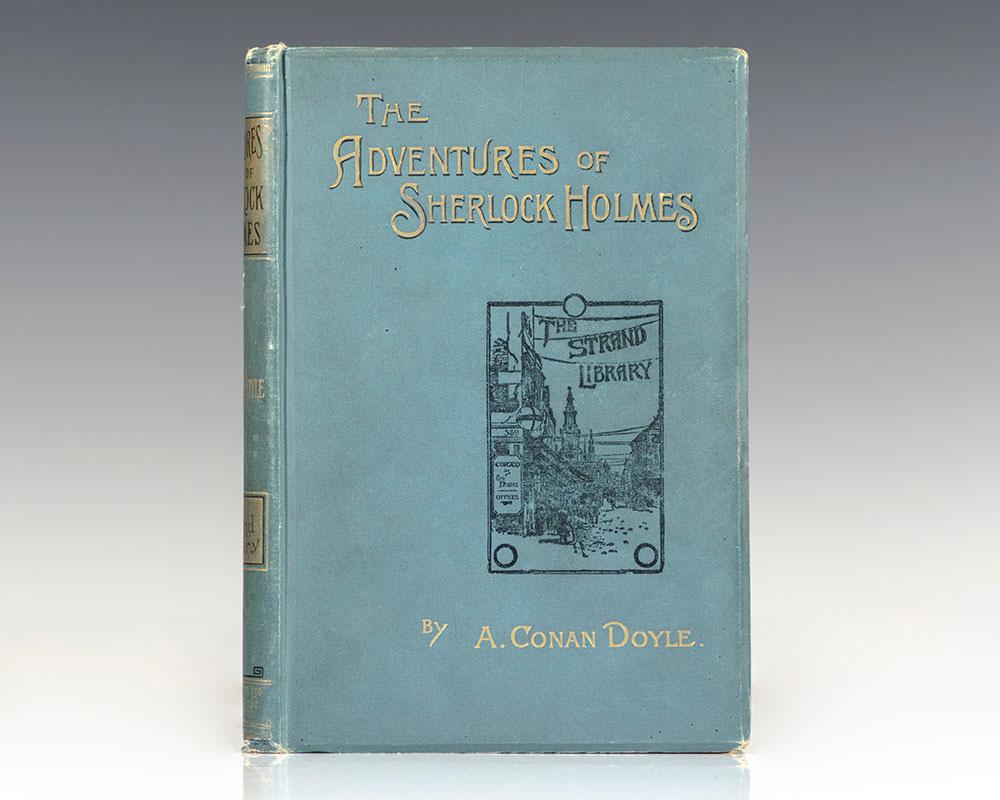
Titelschrift von Erstausgabe "Sherlock Holmes" gesucht
ich suche eine Schrift, die jener der Erstausgabe von A. Conan Doyles "The ADVENTURES of SHERLOCK HOLMES" nahe kommt. Die Erstausgabe stammt von 1892 und wurde in London herausgegeben. Die Illustrationen im Buch stammen von Sidney Paget. Was historische Schriften angeht, bin ich ziemlich hilflos.  Ich habe nun diverse Listen nach Jugendstil und art nouveau durchsucht aber nichts vergleichbares gefunden. Kennt jemand eine Schriftart, die dem nahe kommt?
Wenn jemand eine sofortige Eingebeung bezüglich der Schrift, in dem der Autor geschrieben ist, bin ich auch hier dankbar.
Für »A. Conan Dyole« solltest du unter dem Stichwort »Edwardian« fündig werden. Die »Adventures …« sehen handgemalt aus. Hier könnte dir, wenn nicht »Edwardian«, dann eventuell »Victorian« weiterhelfen.